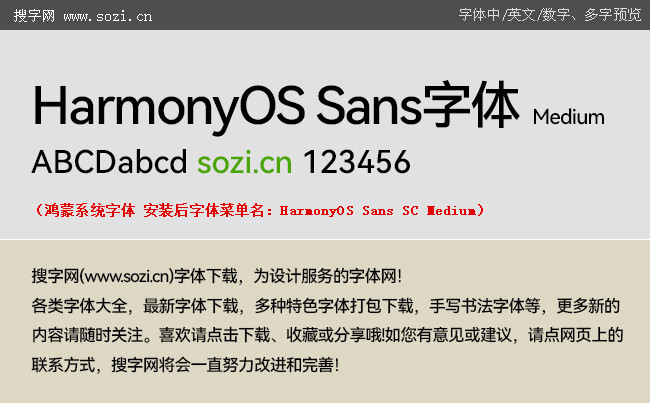
HarmonyOS-Sans字體(鴻蒙字體)-Medium
搜字網(wǎng)給大家提供一款HarmonyOS-Sans字體(鴻蒙字體)-Medium中文字體下載,HarmonyOS Sans字體是華為為HarmonyOS鴻蒙操作系統(tǒng)全新定制的系統(tǒng)默認(rèn)字體。鴻蒙字體設(shè)計(jì)上聚焦于功能性、普適性,是一款多語(yǔ)言的無(wú)級(jí)可變字體。適合應(yīng)用于藝術(shù)設(shè)計(jì)、平面宣傳設(shè)計(jì)、網(wǎng)頁(yè)設(shè)計(jì)等廣告設(shè)計(jì)。